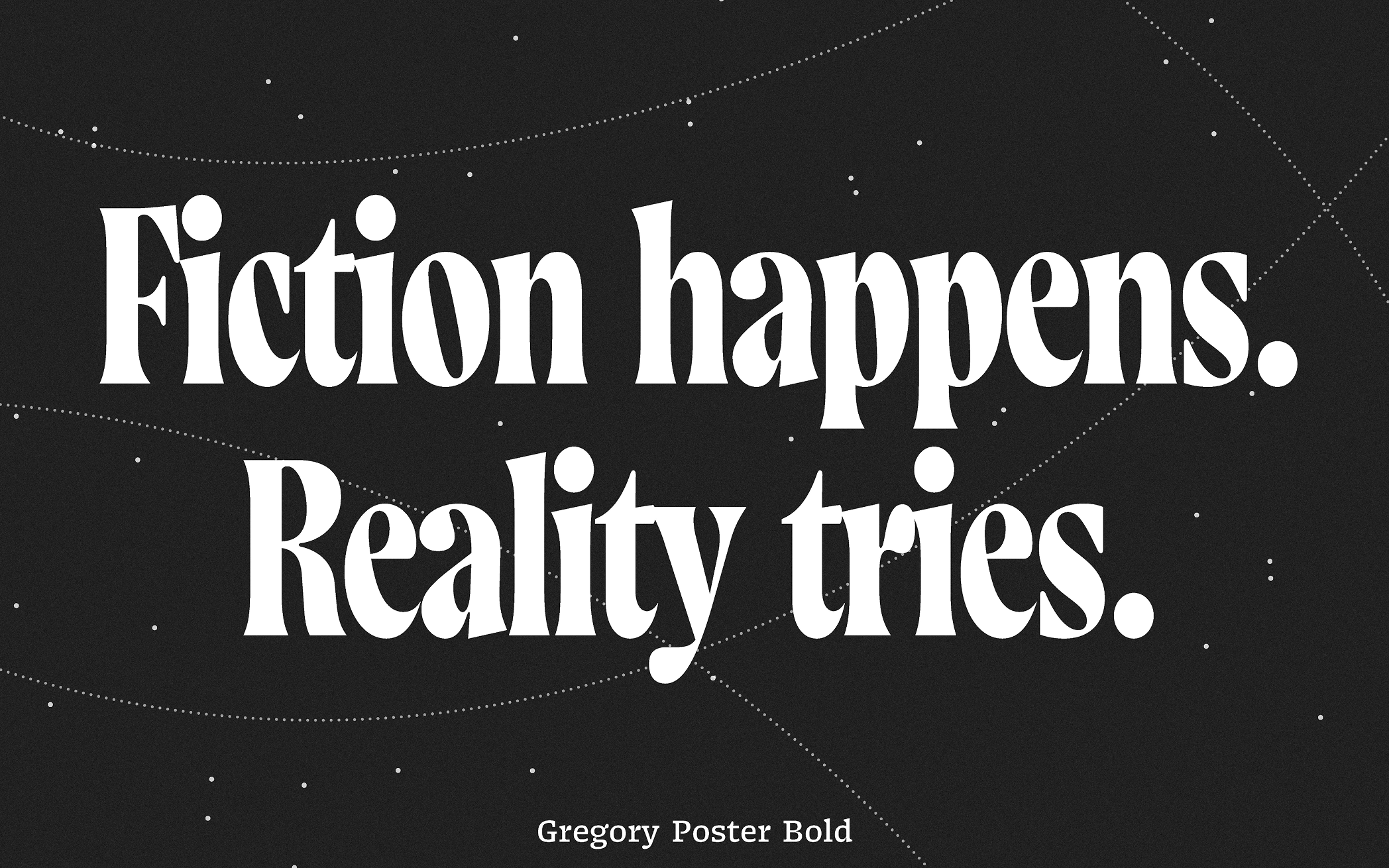
Gregory Poster — шрифт для разговоров о провокационном искусстве, сказок о параллельных мирах или дискуссии о том, что же такое настоящая красота. В нём нашлось место и ностальгической романтике, и ярким деталям.
Gregory Poster вдохновлен леттерингом с обложек винтажных книг. И хотя его нельзя отнести ни к одной из существующих категорий шрифтов, расклёшенные штрихи, контраст и наклон диагоналей делают Gregory почти барочной антиквой.
Фрагмент обложки книги «Humpty-Dumpty William & Co». De Vinne Press, 1916
Gregory Poster говорит на 270 языках, включая вьетнамский, сербский и македонский, оснащён чувствительной к регистру пунктуацией, набором иконок, табличными и минускульными цифрами, верхними и нижними индексами, а ещё двумя наборами обрамлённых
Автор Gregory Poster — сооснователь студии TypeMates Якоб Рунге, кириллицу добавил Серёжа Рассказов, а греческий — Георг Триандефиллакас. Также в работе над шрифтом принимали участие Криста Радоева, Натали Раух, Оксана Шайнман и Япрак Бусе.